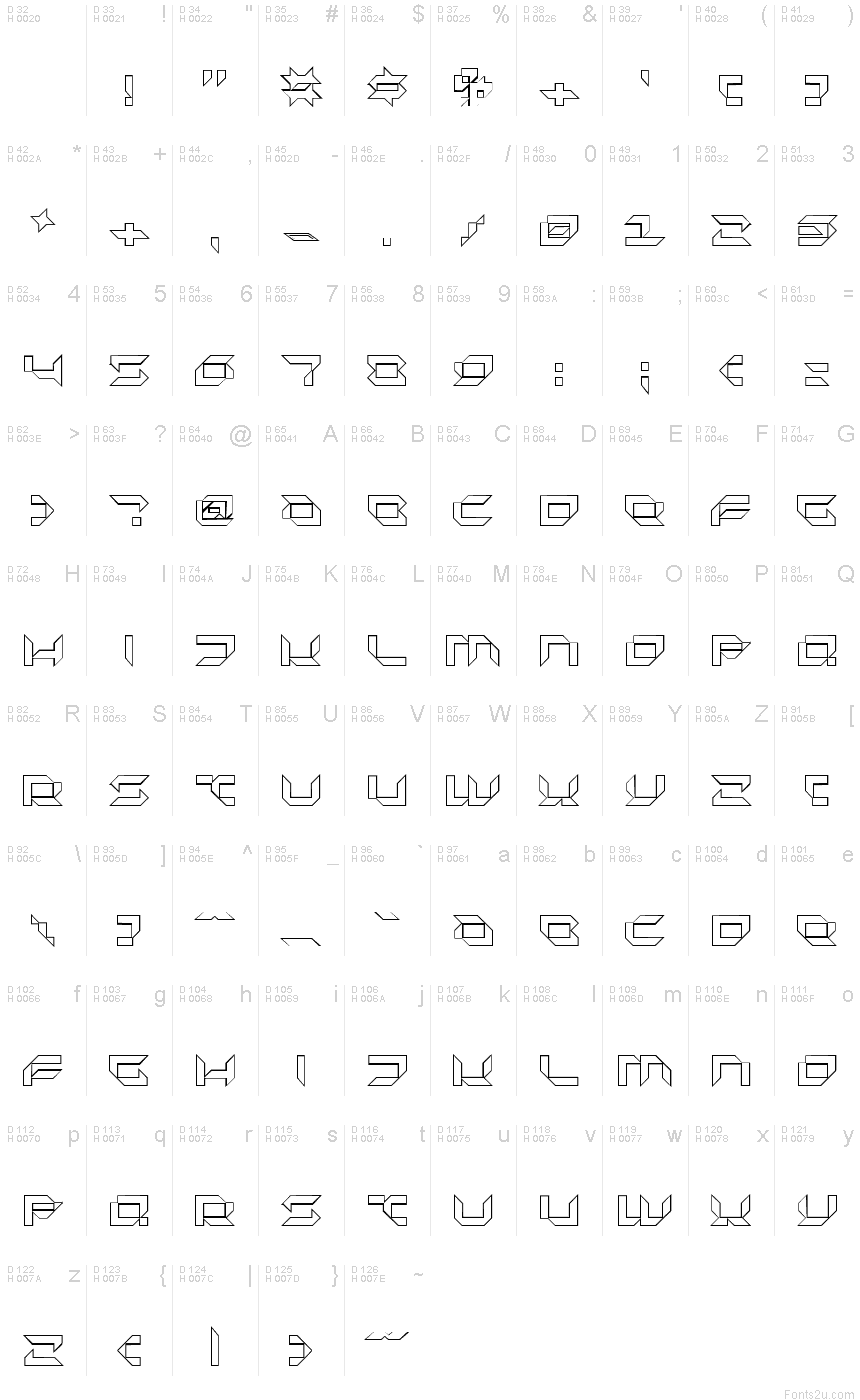
Pluranon Stroke, autorstwa Milana Zrnica i Tommy'ego Cary'ego, to darmowy, futurystyczny font typu display, wyróżniający się ostrym, technicznym charakterem. Litery sprawiają wrażenie zbudowanych z twardych linii i ściętych narożników. Dzięki otwartym, linearnym formom przywodzą na myśl interfejsy sci-fi, grafikę pojazdów czy cyfrową sztukę koncepcyjną, wykraczając poza standardowe kroje nagłówkowe.
Najlepiej sprawdza się wszędzie tam, gdzie alfabet staje się strukturą graficzną: plakaty, branding gier, ulotki techno, nagłówki oraz opakowania produktów elektronicznych czy odzieży streetwear idealnie pasują do tego darmowego fontu. Użyj go w krótkich tytułach, logotypach i monogramach, gdzie konturowa konstrukcja dodaje lekkości, a kanciasty rytm robi całą robotę.